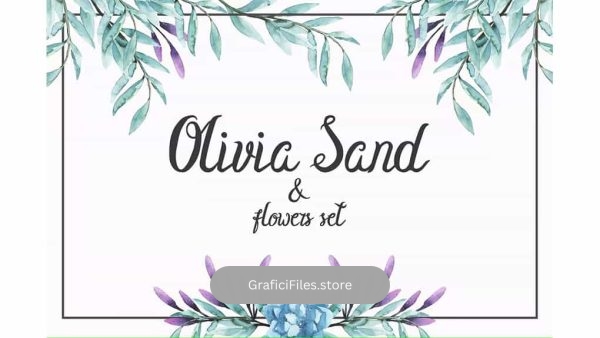
دانلود فونت انگلیسی Olivia Sand Typeface & Flowers set
فونت انگلیسی Olivia Sand : این مجموعه شامل 21 فایل PNG با گل های آبرنگ زیبا برای لوگو، دعوت نامه و 1 فونت دست نویس میباشد. این مجموعه برای دعوت نامه، کارت پستال، های بسته بندی، وب سایت ها و … مناسب است.
• عنوان مجموعه: Olivia Sand Typeface & Flowers set
• سبک: Sans-Serif
• فضا بین حروف: معمولی
• اندازه بهینه: تمامی سایز ها